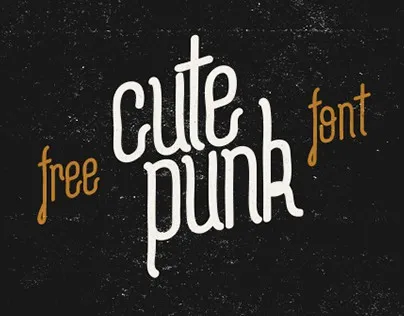
Cutepunk Typeface – Download Grátis
Introduzimos Cutepunk Typeface. Este é um tipo de letra muito bold e jovial que certamente vai te encantar. Cutepunk foi criado por Hamilton e disponibilizado pela flou, permitindo a utilização em qualquer tipografia combinando pares de letras para personalizar seus designs ou escolhendo suas melhores frases preferidas para adicionar às imagens. Este tipo de letra traz consigo uma dose extra de personalidade, adaptável a diferentes contextos e estilos de design. Sem dúvida, Cutepunk será um recurso útil na sua coleção de fontes digitais, adicionando um toque único aos seus projetos.